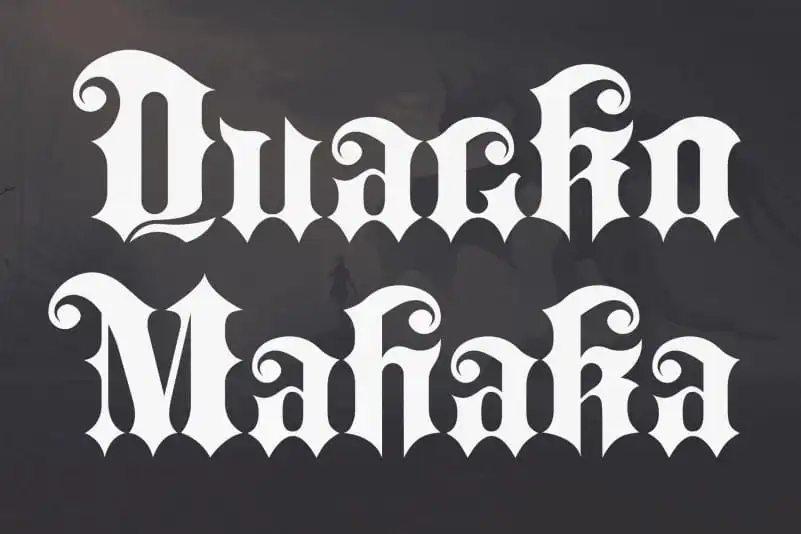
Quacko Mahaka Blackletter Font – Download Grátis
A Quacko Mahaka Blackletter Font é uma tipografia autêntica e poderosa que adiciona um toque distintivo a qualquer projeto criativo. Com seus traços arredondados e curvaturas elegantes, essa fonte blackletter oferece uma qualidade de acabamento sofisticado. Perfeita para artes de parede bonitas, postagens do Instagram emocionantes, exposições, logotipos de mídia social, anúncios, embalagens de produtos, designs de produtos, rótulos, fotografias e marca d’água, a Quacko Mahaka Blackletter Font é um elemento indispensável para qualquer projeto. Seja você designer gráfico, editor de imagens ou produtor de conteúdo digital, essa fonte vai transformar suas ideias em algo verdadeiramente único e memorável. A sua busca por uma font blackletter poderosa e elegante acabou!